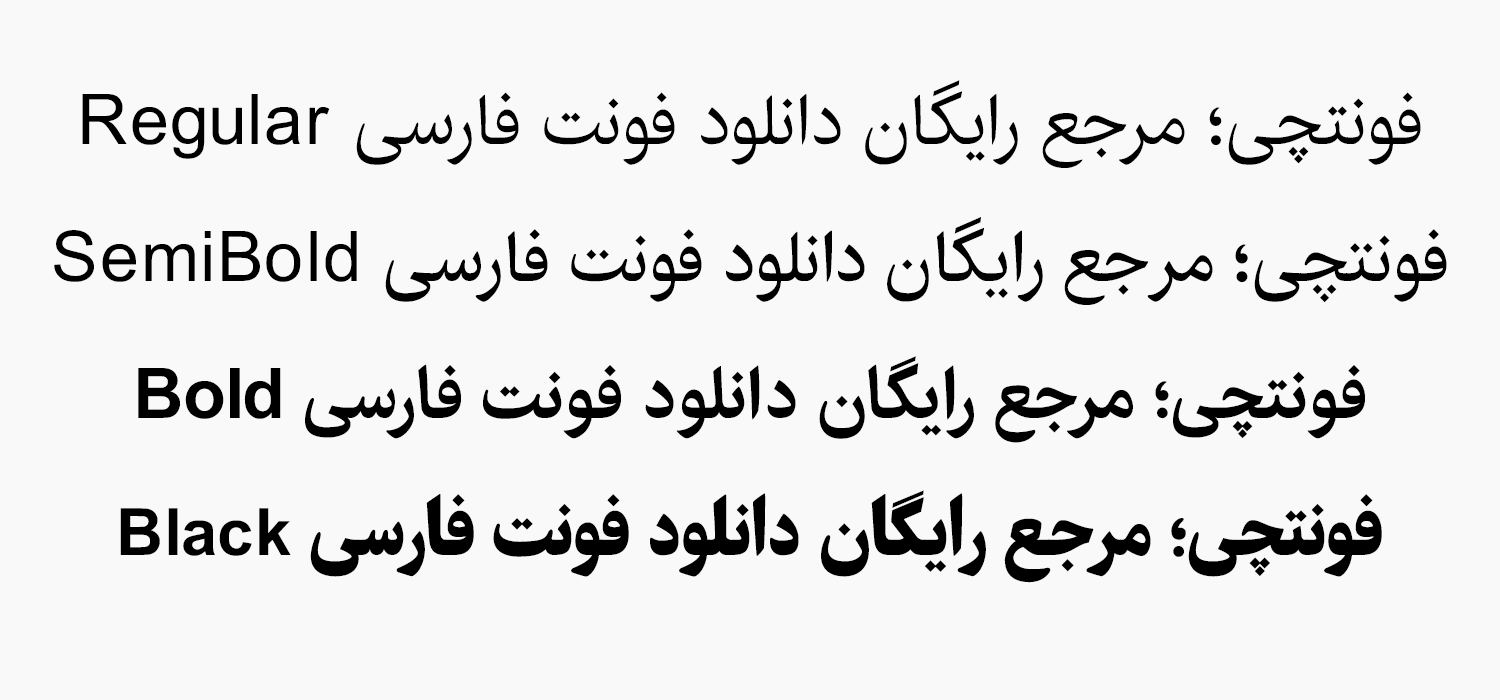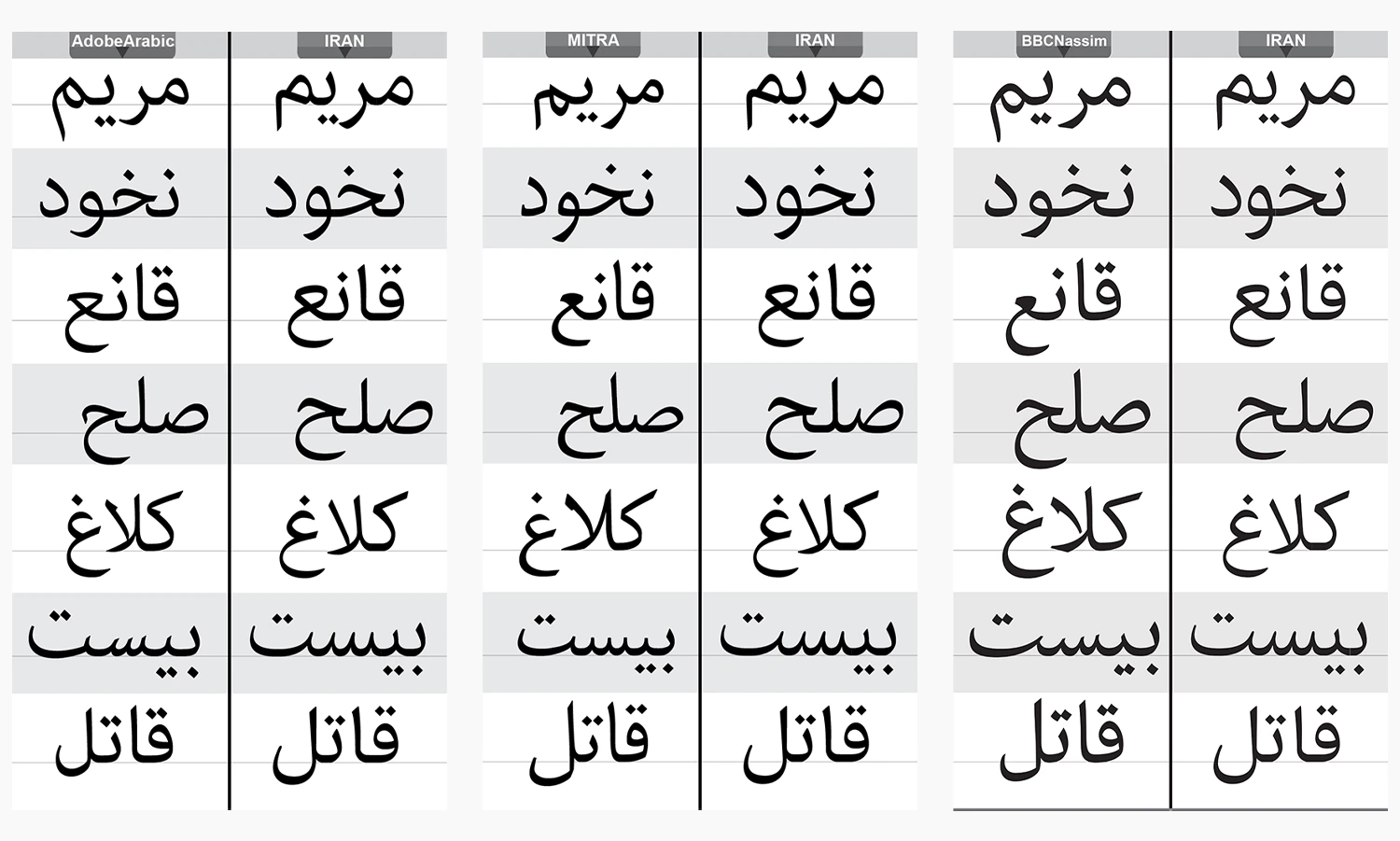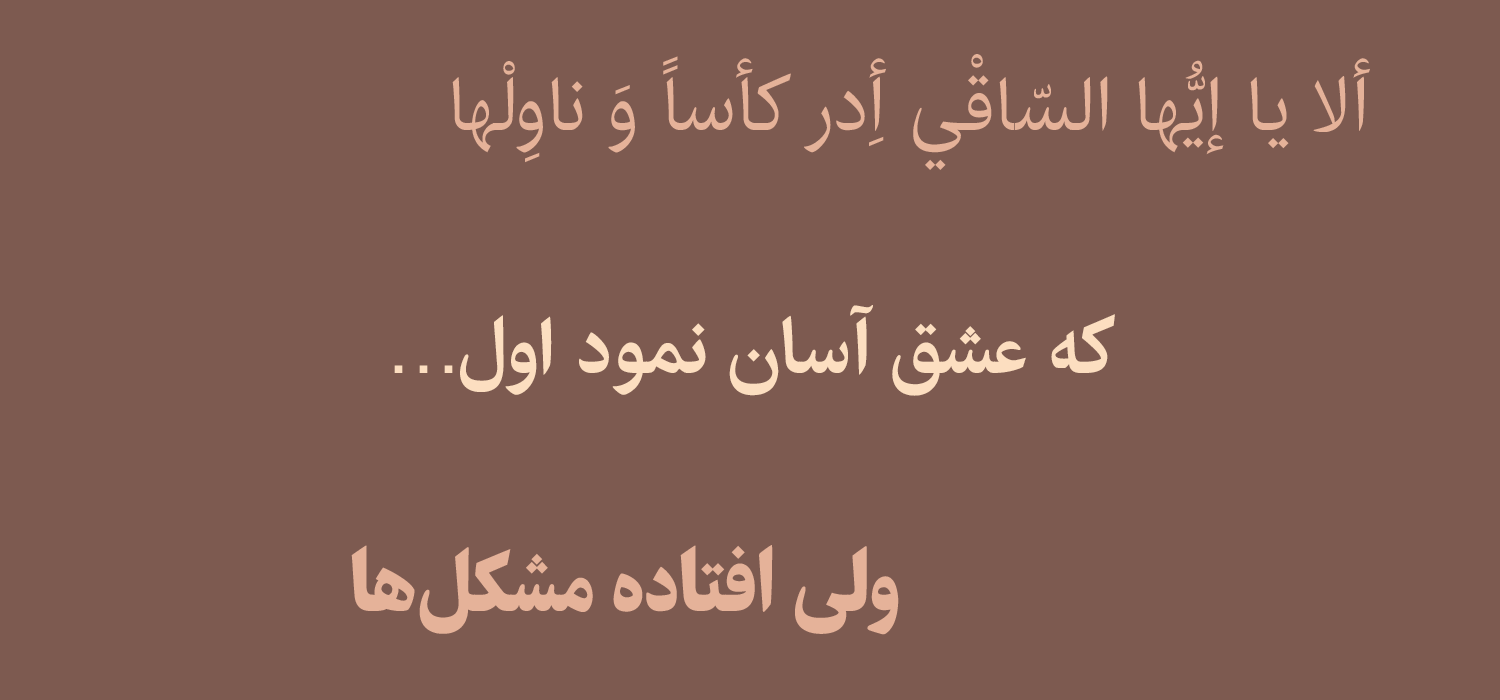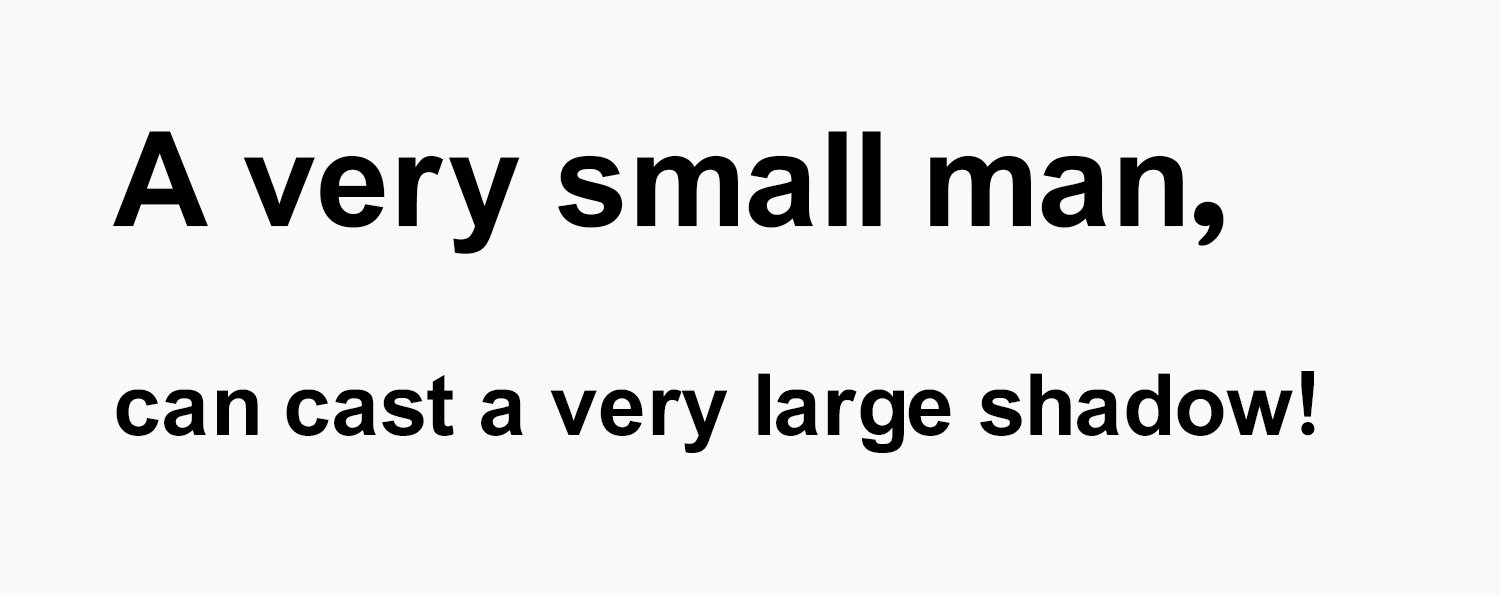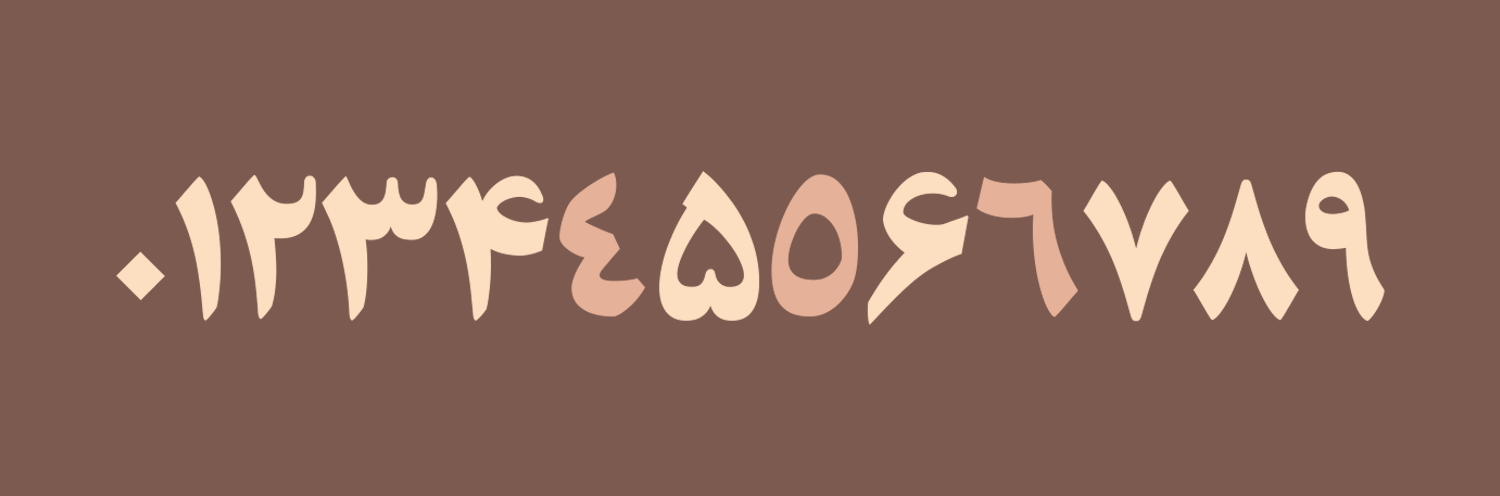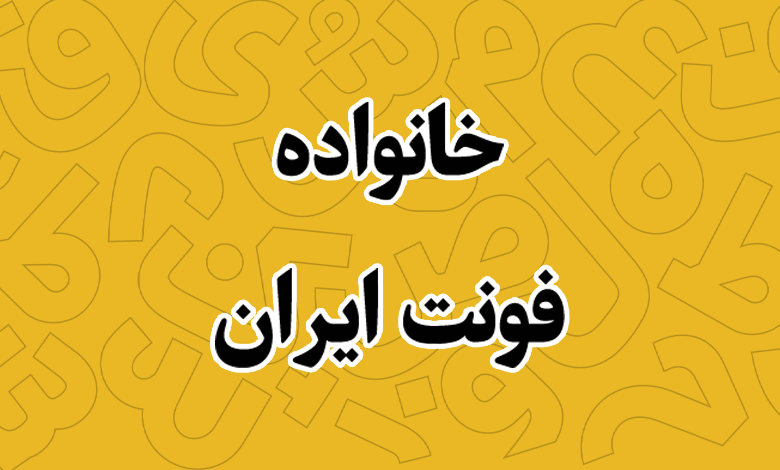
فونت خانواده ایران (Iran Family)
خانواده فونت ایران یا فونت ایران (به انگلیسی: Iran Family) فونت رایگان و مناسب مطبوعات است که از ۴ وزن مختلف پشتیبانی کرده و با توجه به ویژگیهایی که دارد میتوانید از این قلم برای متون طولانی استفاده کنید.
این قلم از آنجایی نام «خانواده فونت ایران» یا یدک میکشد که در کارگاه طراحی تایپفیس توسط هدی ترابی خواه و سنا میلانی، زیر نظر مسلم ابراهیمی در چند وزن مختلف طراحی شده است.
در ادامه این نوشته از سایت فونتچی به نقد و بررسی فونت ایران خواهیم پرداخت؛ قلمی کاملا رایگان بر پایه خط نسخ که میتوانید از آن در مطبوعات و برای متون طولانی استفاده کنید. این فونت جزو فونتهایی است که در سالهای گذشته که خبری از تنوع فونت زیاد برای زبان فارسی وجود نداشت ساخته شده و برای استفاده در فضای چاپ تا دیجیتال (وب فونت) مناسب است.
بررسی و دانلود فونت ایران (Iran Family)
در این قلم تلاش شده تا حروف بر اساس سبک معاصری با حال و هوای فونتهای رایج فارسی آن زمان همچون زر، میترا و نازنین ایجاد شود که مشکلات آنها را پوشش داده و ضمن آن دارای خوانایی مناسبتری باشد.
توسعه خانواده فونت ایران متوقف شده است و هماکنون بیش از یکسال است که این فونت در نسخه جدیدی با تغییرات گسترده وزنی، پشتیبانی از سبکهای مختلف و نسخه وریبل دارد که به نام فونت فرهنگ منتشر شده است.
این تایپفیس مشابه با سایر قلم هایی که بر وزن نسخ هستند برای استفاده در مطبوعات و چاپ بهترین بهرهوری را دارد که میتوانید با توجه به وزنهای متعددی که دارد در تمامی بخشهای متون خود از آن استفاده کنید.
سبک طراحی و وزن فونت ایران
خانواده فونت ایران بر پایه خط نسخ و با تلفیقی از چند فونت مختلف مثل زر، نازنین و میترا ایجاد شده است که در مقایسه با آنها دارای خوانایی بیشتر، سطر و ستونبندی استانداردتری است. علاوه بر این کاراکترهای بیشتری را شامل بوده و با توجه به پشتیبانی چندزبانهای که دارد طیف وسیعی از نیازها را خصوصا در صنعت چاپ و کتب پوشش خواهد داد.
این فونت در ۴ وزن معمولی (Regular)، کمی بولد (SemiBold)، بولد (Bold) و سیاه (Black) در دسترس است که از ۴ فرمت رایج TTF, EOT, WOFF و WOFF2 پشتیبانی کرده و با توجه به چنین مشخصاتی برای طیف وسیعی از نیازها کاربرد دارد که در ادامه بیشتر با آنها آشنا خواهیم شد.
پشتیبانی کامل از ۵ زبان متنوع
در بین فونتهای رایگان فارسی خانواده فونت ایران یکی از معدود قلمهایی است که از چندین زبان متنوع پشتیبانی میکند و چنین ویژگی مشابه با سایر فونتهای پرمیوم، مرهون رسم خط فارسی است که در چندین زبان خاورمیانه ای وجود دارد.
زبانهایی نظیر عربی، کردی، ترکی (با رسم خط فارسی) و زبان اردو جزو این موارد هستند که فونت ایران پشتیبانی کاملی از حروف، اعراب، اعداد و کاراکترهای خاص را در این زبانها در خود جای داده است.
در این قلم اعراب در همنشینی کاملا مناسب و درستی روی حروف قرار گرفته و همراه شدن آنها با سایر کاراکترهای سکون، همزه یا تشدید موجب به هم ریختگی نمیگردد. جدایی از این ساختار مناسب و نسخگونهای دارند که به زیباتر کردن حروف و کلمات نیز کمک میکند.
حروفی همچون «ک، ی، ه، ؤ، ئ» در زبان عربی که متفاوت از شکل فارسی هستند گلیف اختصاصی خود را دارند. یا در زبان اردو حروفی مانند «ﮧ، ﮩ، ے» نیز گلیف خاص خود را دارند که با قرارگیری زبان صفحه کلید روی آنها امکان تایپ آنها را خواهید داشت.
این قلم از نسخه انگلیسی نیز پشتیبانی میکند که در آن از فونت اپن سورس استفاده شده که دارای ساختاری سیاه به این قلم است.
دارای اعداد فارسی هک شده و استاندارد
خانواده فونت ایران از اعداد به شکل حرفه ای پشتیبانی می کند. به طوری که اعداد بر مبنای زبان صفحه کلید تایپ خواهند شد. یعنی زمانی که زبان فارسی باشد تایپ اعداد فارسی و برای زبان عربی نیز امکان تایپ اعداد عربی را که اعداد «۴۵۶» ظاهری متفاوت دارند را در اختیار خواهید داشت.
بنابراین صفحه کلید شما روی هر زبانی غیر از فارسی قرار داشته باشد یا از بخش اعداد ماشین حساب کیبورد استفاده کنید، در هر شرایطی اعداد فارسی تایپ خواهند شد. چنین ساختاری برای توسعه نرمافزاری و وب فونت مناسب است که بدون نیاز به استفاده از ترفندهایی بر پایه زبان جاوا و… بخواهید از اعداد فارسی استفاده کنید.
مناسب مطبوعات و متن طولانی
قلم فونت ایران دارای ۴ وزن مختلف معمولی تا سیاه است که در مطبوعات استفاده از چنین وزنهایی را بهوفور میبینیم. چه در صفحه یک روزنامه که هر روز با آن سر و کار دارید یا مجلهای سرگرم کننده مطمئنا در بخشهای مختلف صفحه از وزنهای مختلف یک قلم استفاده خواهد شد.
وزن سیاه این قلم میتواند برای عناوین مورد استفاده قرار گیرد که ذهن خواننده را جذب عنوان نماید. سایر وزنها نیز میتوانند متناسب با تیتر و ساختاری که سایر بخشهای محتوای مطبوعات دارد تقسیم بندی شوند.
این فونت برای طراحی جلد کتب و همچنین فونت متن کتابها بسیار مورد استفاده قرار گرفته است که مطمئنا در زندگی روزمره خود با آن سر و کار داشتهاید.
از این قلم همچنین میتوانید به عنوان طراحی رابط کاربری در اپلیکیشن های موبایل یا استفاده به عنوان فونت گوشی خود بهره لازم را ببرید. خصوصا اینکه امکان استفاده از آن را در برنامههای موبایل نظیر اینشات برای کارهای گرافیکی نیز خواهید داشت.
آخرین نسخه فونت ایران ورژن ۴.۱ است که چند سالی است از انتشار آن میگذرد. این فونت همانطور که در ابتدا گفته شد حالا تحت عنوان فونت فرهنگ آپدیت شده است که شامل وزنهای بیشتر و پشتیبانی از چند سبک مختلف است.